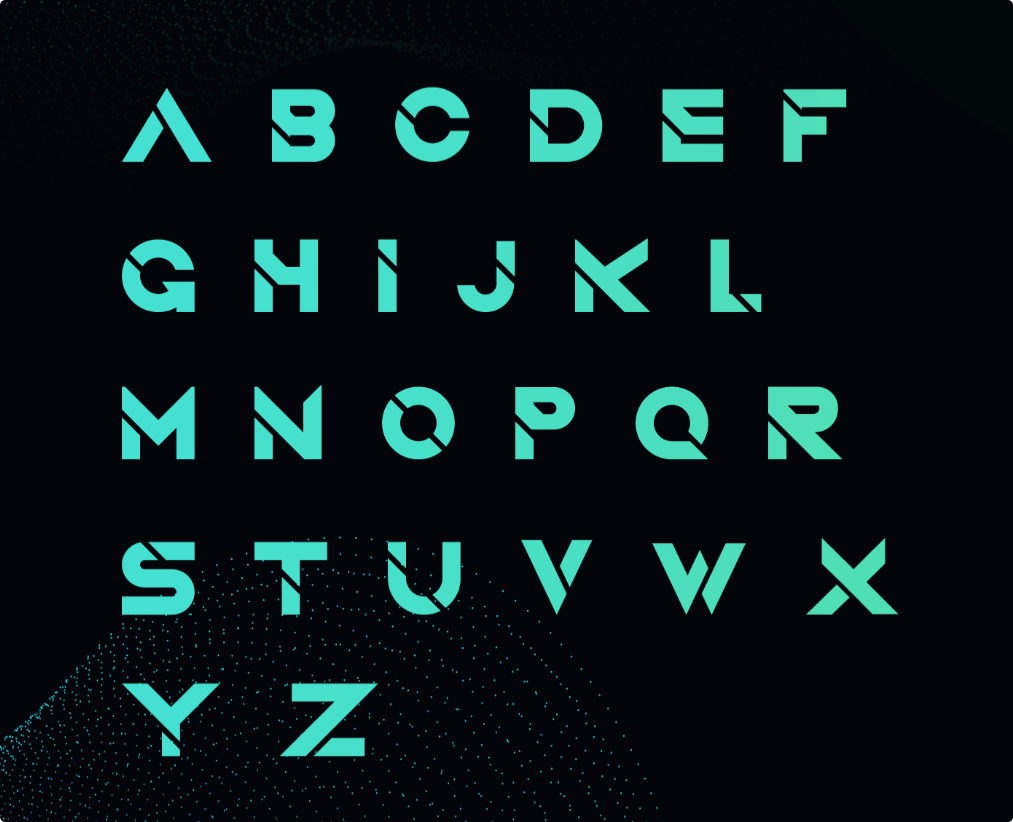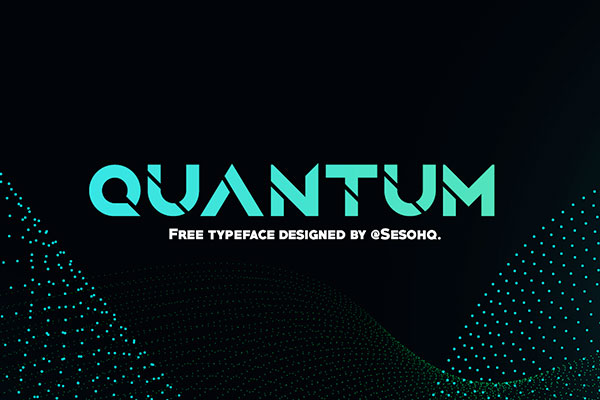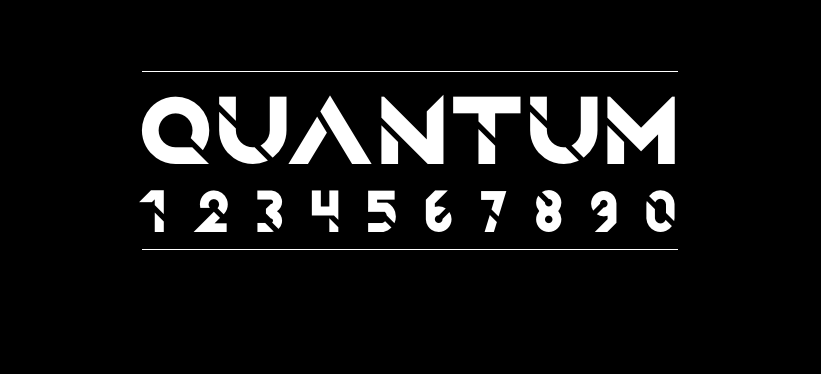
QUANTUM
QUANTUM字体介绍
QUANTUM是由Greg ‘Sesohq’ Ortiz’s 创建的大胆字体。这种独特的字体是受形状生成器工具和大胆的口音启发的。它在字母的原始笔画上进行削减和未来派设计,非常适合与游戏,空间,未来,科幻等相关的任何事物,并且非常适合徽标,品牌和标题。
QUANTUM字体应用示例